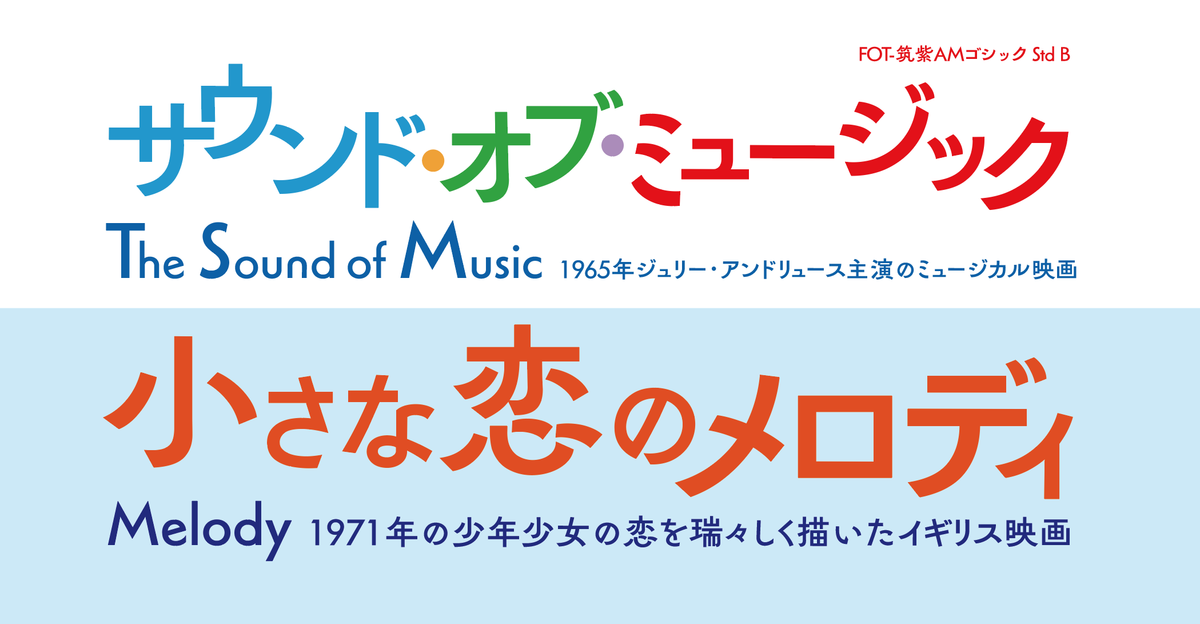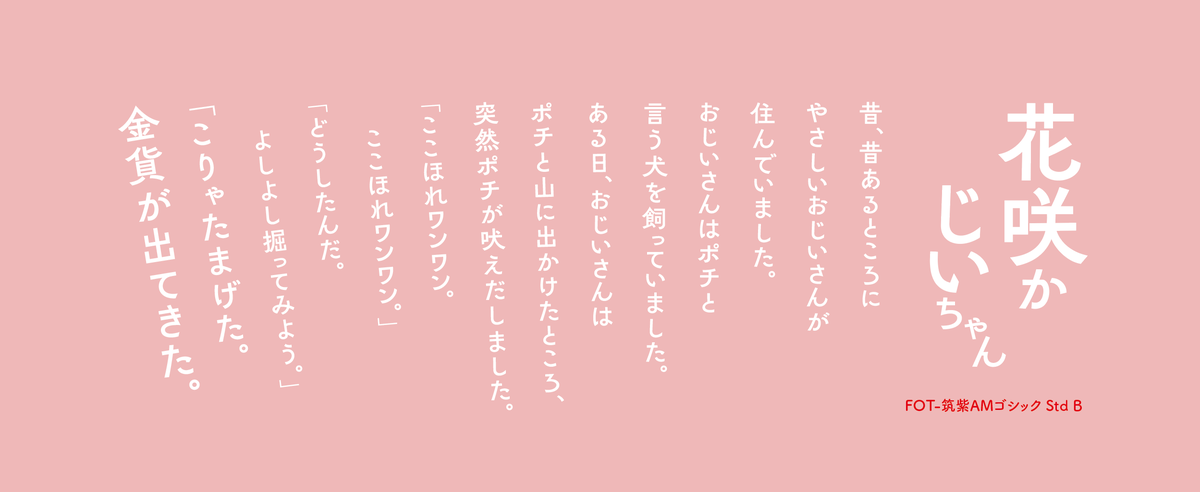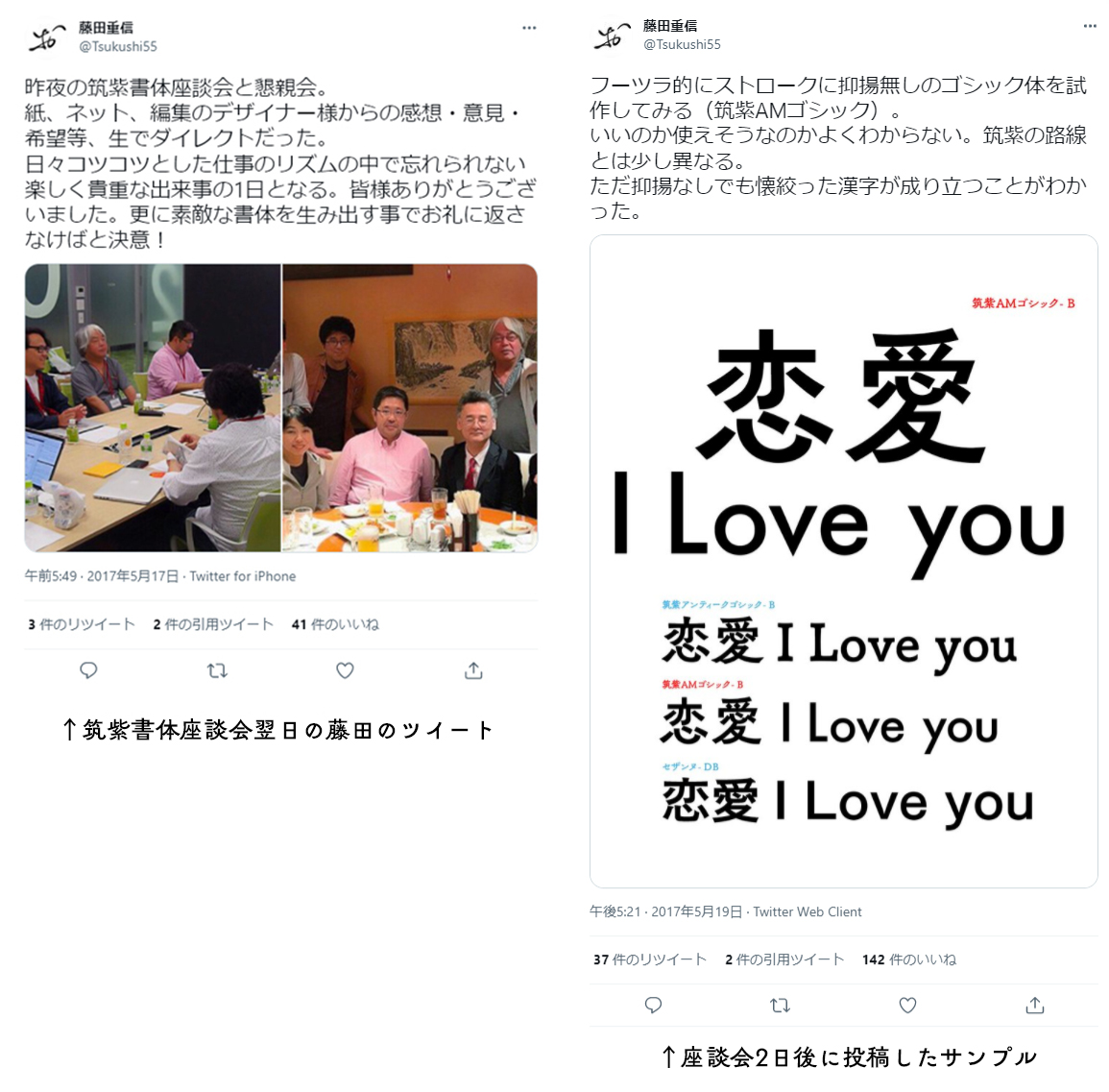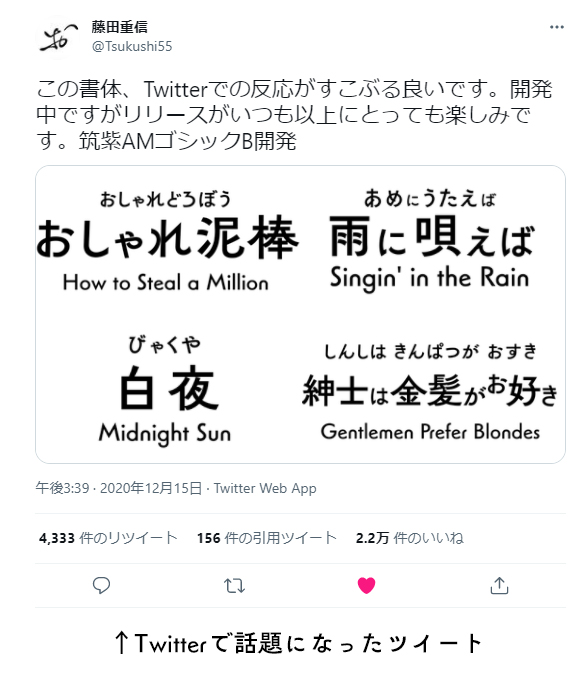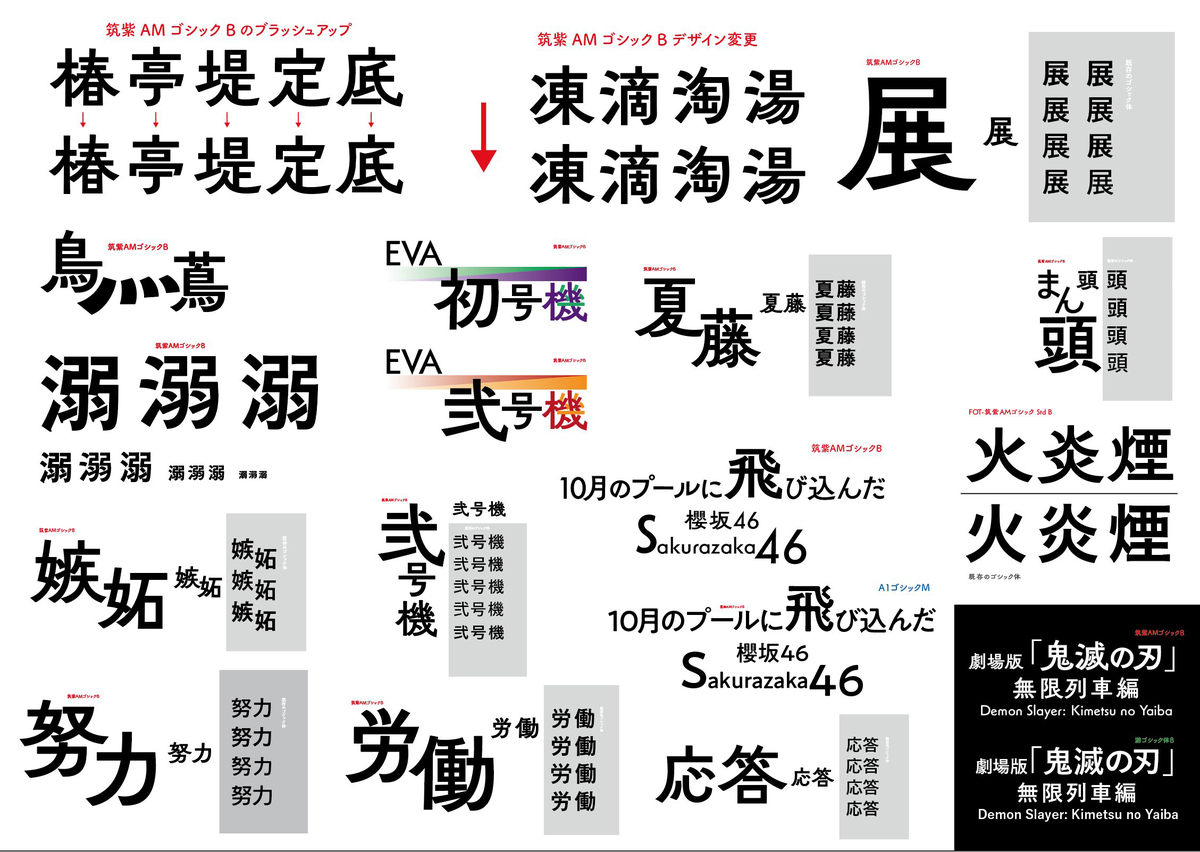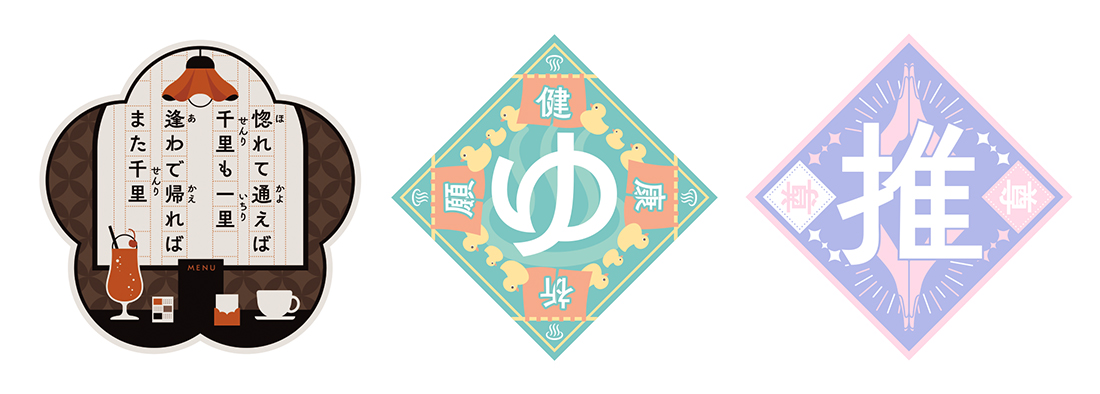
筑紫AMゴシック
フォントワークスは、2022年3月23日(水)に、藤田重信氏デザインによる、フォントワークスのフラッグシップフォントである筑紫書体シリーズの最新作で、古くて新しいエモーショナルな新書体「筑紫AMゴシック」をリリースしたを発表した。
「筑紫AMゴシック」書体説明
「筑紫AMゴシック」は、アンティークな骨格を持ち、スッキリとしたモダンなエレメントでデザインした角ゴシック体となる。今までの金属活字の流れを受けたオールドな角ゴシック体や、近年のモダンな角ゴシック体とは一線を画した、新鮮な空気感をコンテンツに纏わせる「革新的な書風」。
「筑紫AMゴシック」開発背景
SNSのコミュニケーションからブラッシュアップされていった、「古くて新しい」エモーショナルな書体。
「筑紫AMゴシック」』は、2017年5月の「筑紫書体座談会」からすべてが始まった。
複数のクリエイターや装丁デザイナーが参加された本座談会の中で、フォントワークスの書体デザイナー・藤田重信氏へ「何故、FuturaⓇに合う日本語のゴシック体がないのでしょうか?」という問いかけがあり、その質問にインスピレーションを得た藤田はすぐに試作を作成し、SNSに投稿。大きな話題を呼んだ。
そこから約5年の歳月を経て、遂に『筑紫AMゴシック』が完成した。
文字自体はジオメトリック(幾何学的)な印象でありながら、骨格は「オールド」かつ、どこか「エモーショナル」で情緒を感じさせる。これを藤田重信氏は「古くて新しい」と言う。
他の角ゴシック体にはない魅力を持った「筑紫AMゴシック」は、これからのニュースタンダードとなるかもしれない。